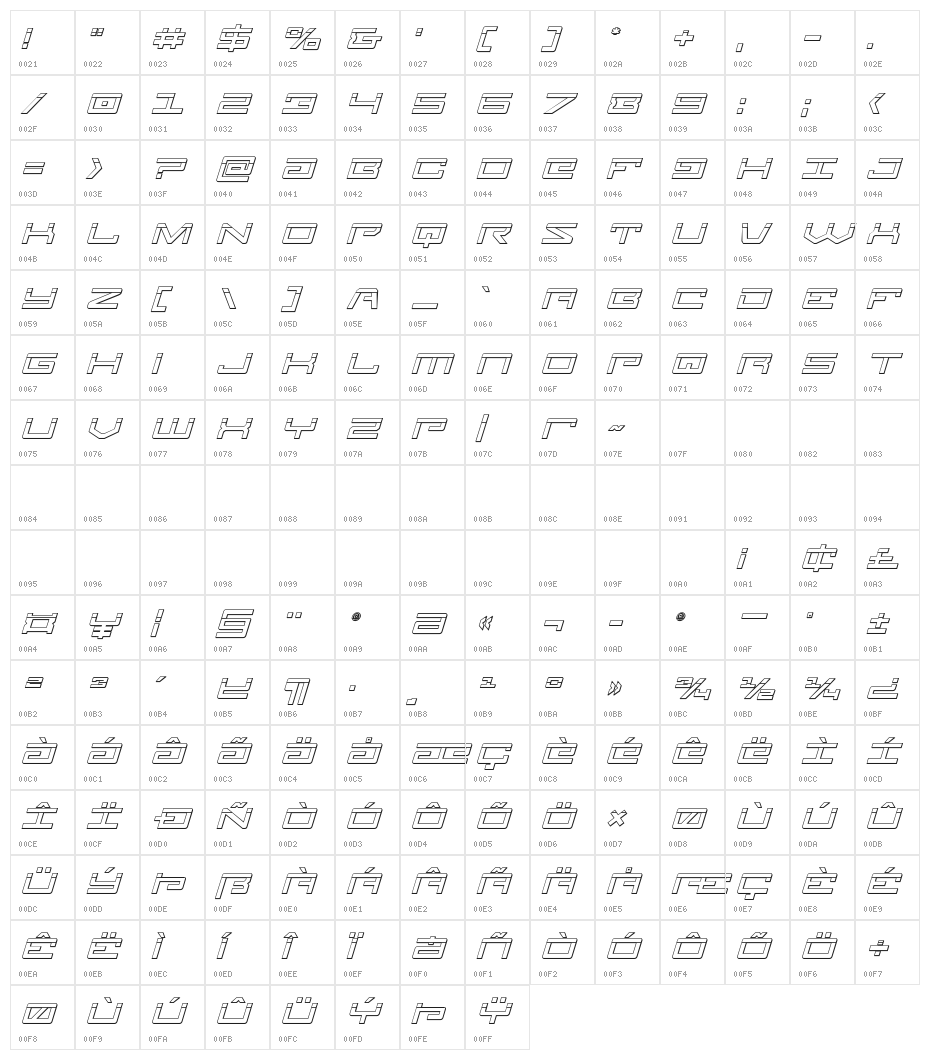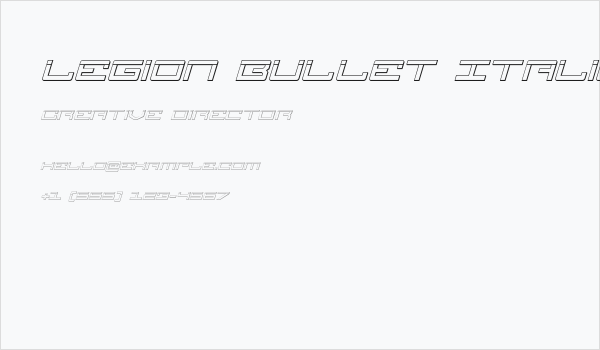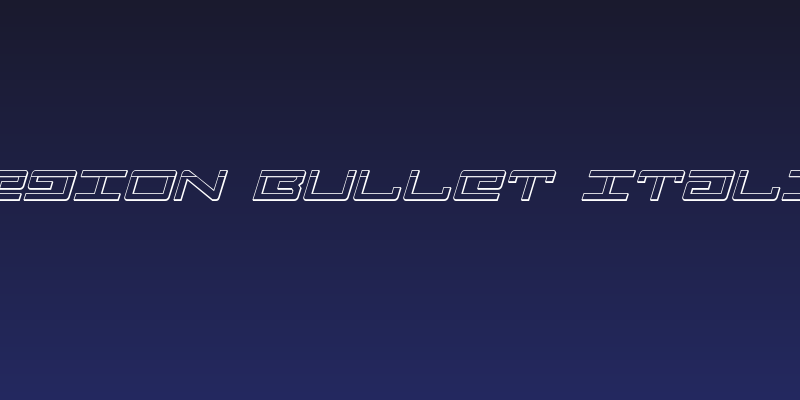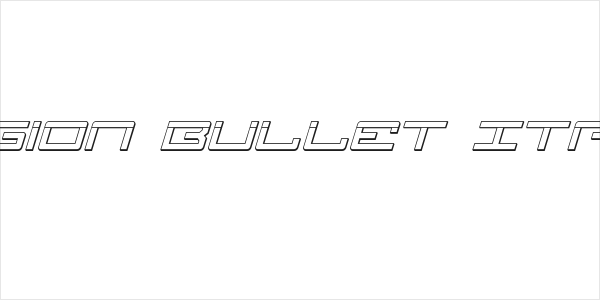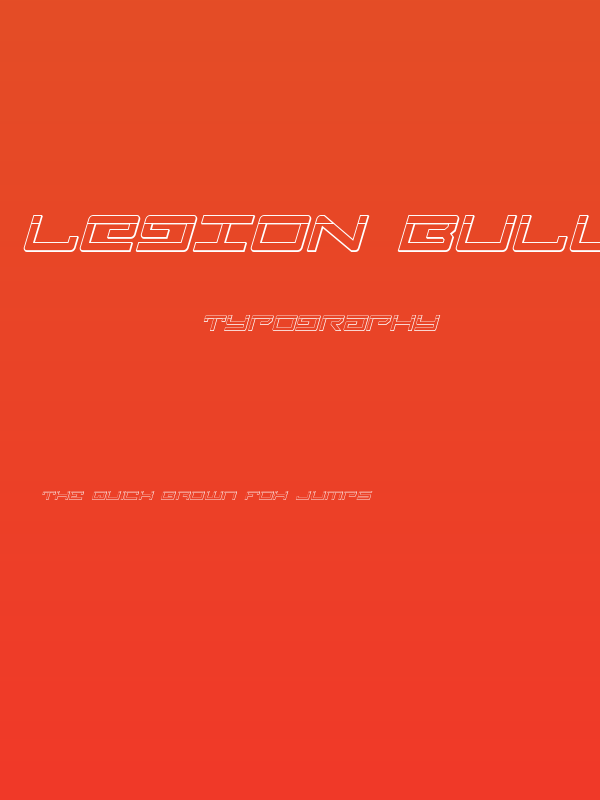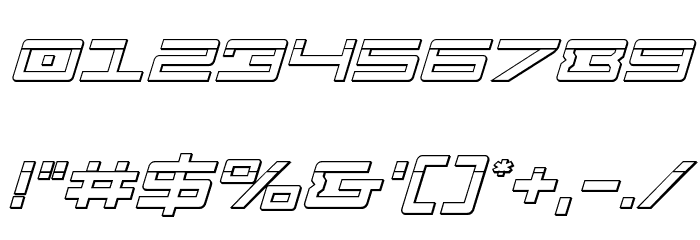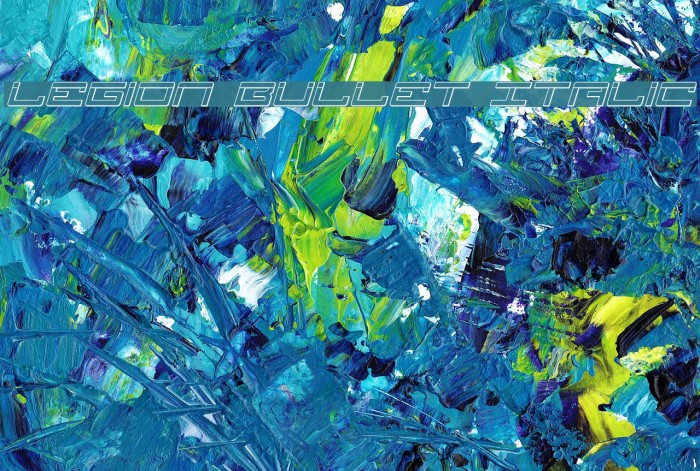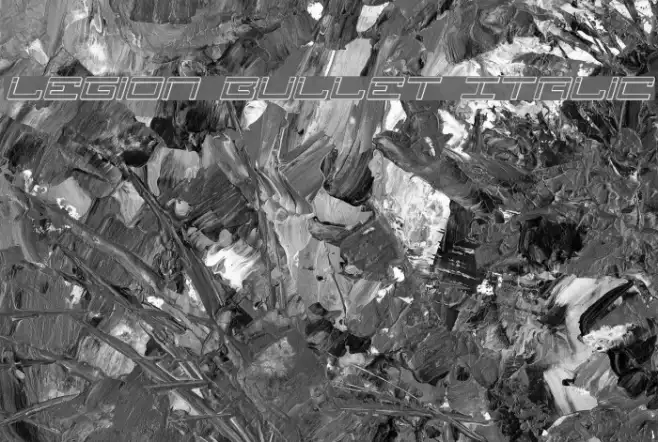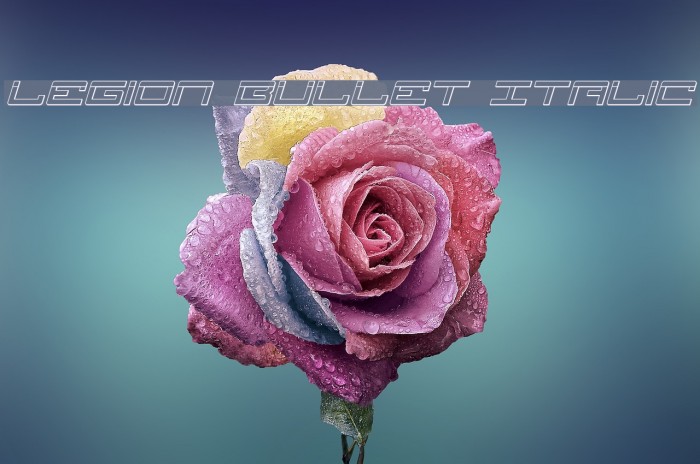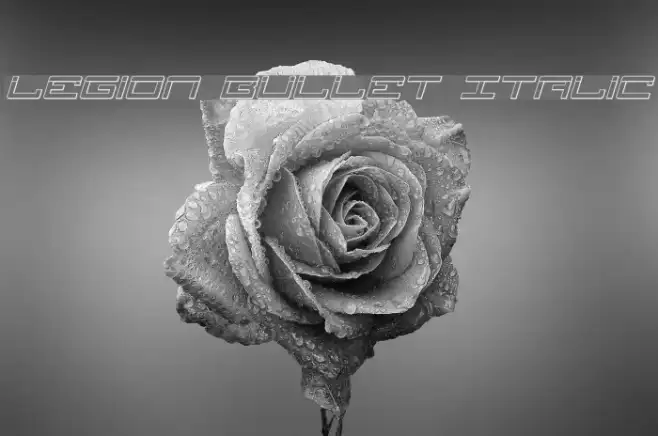
Legion Bullet Italic Font
✎ Outline
| Vorgeschlagene Projekte | Ideal for technology branding, sci-fi movie posters, video game titles, and modern advertising campaigns. |